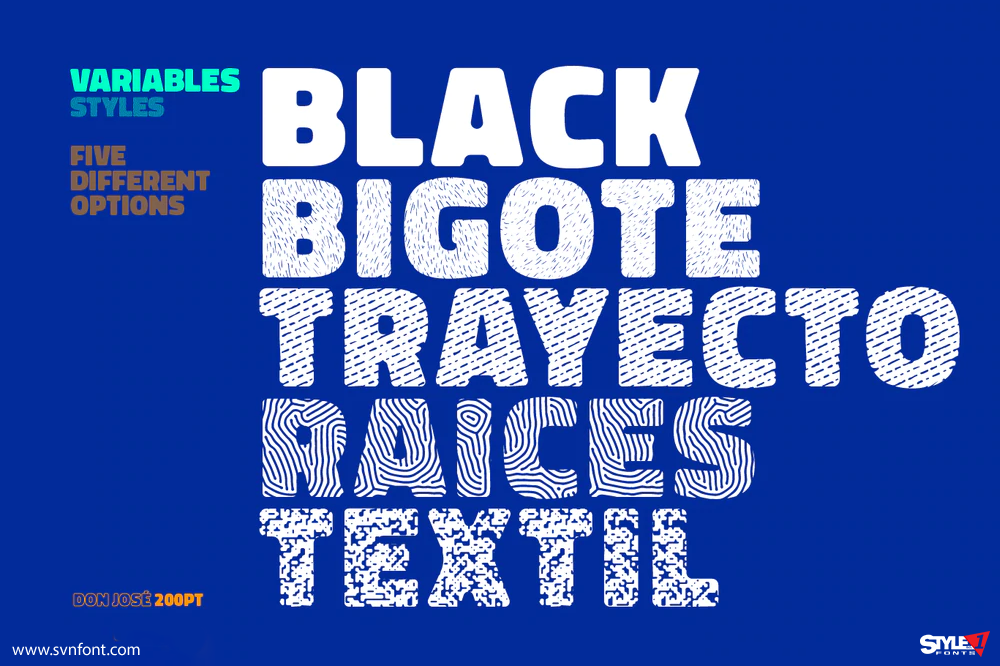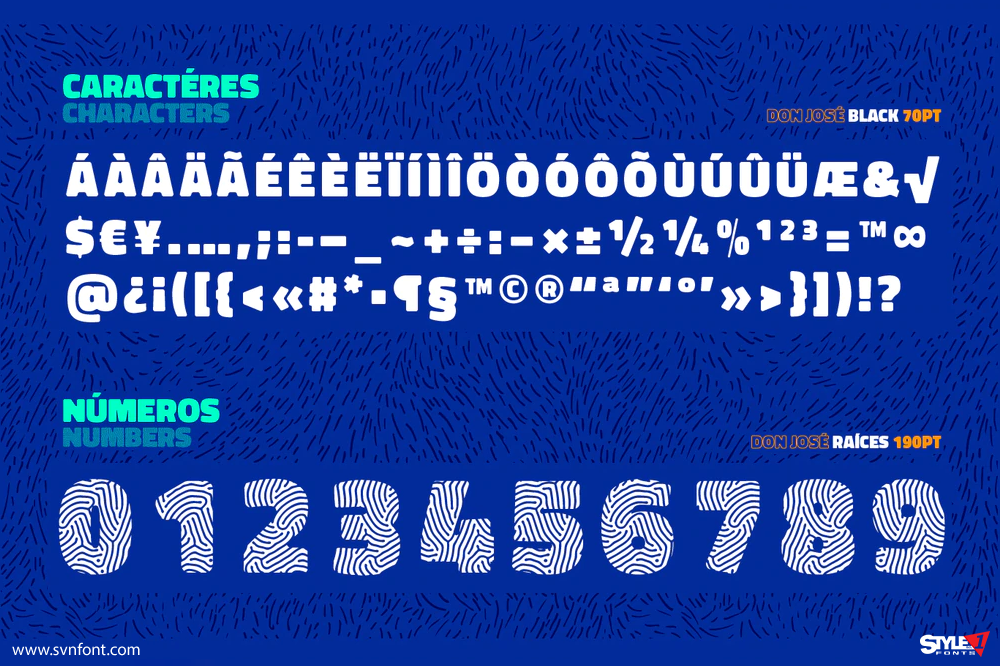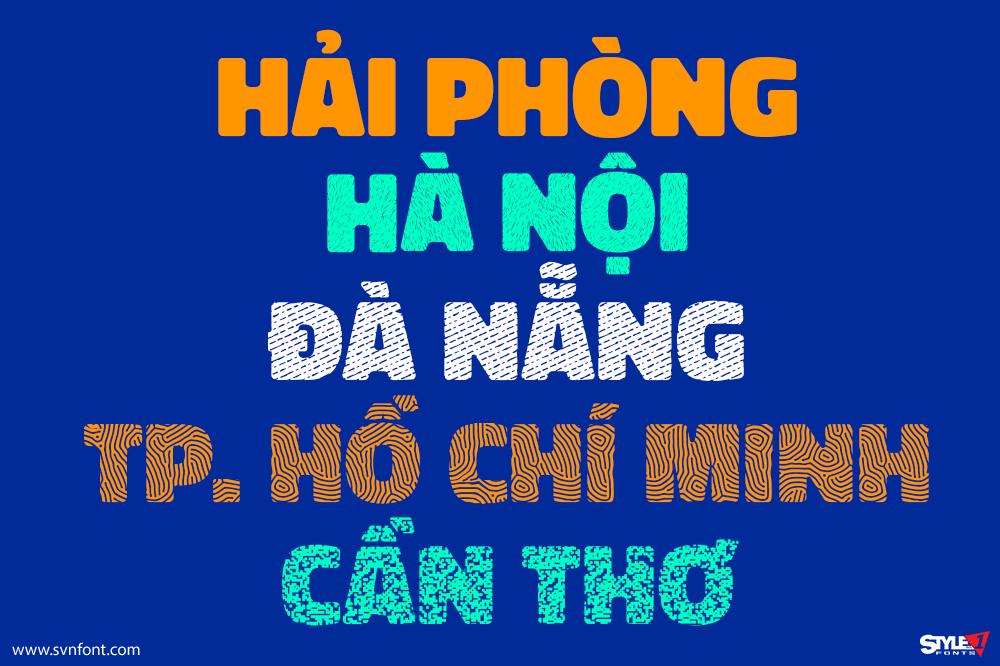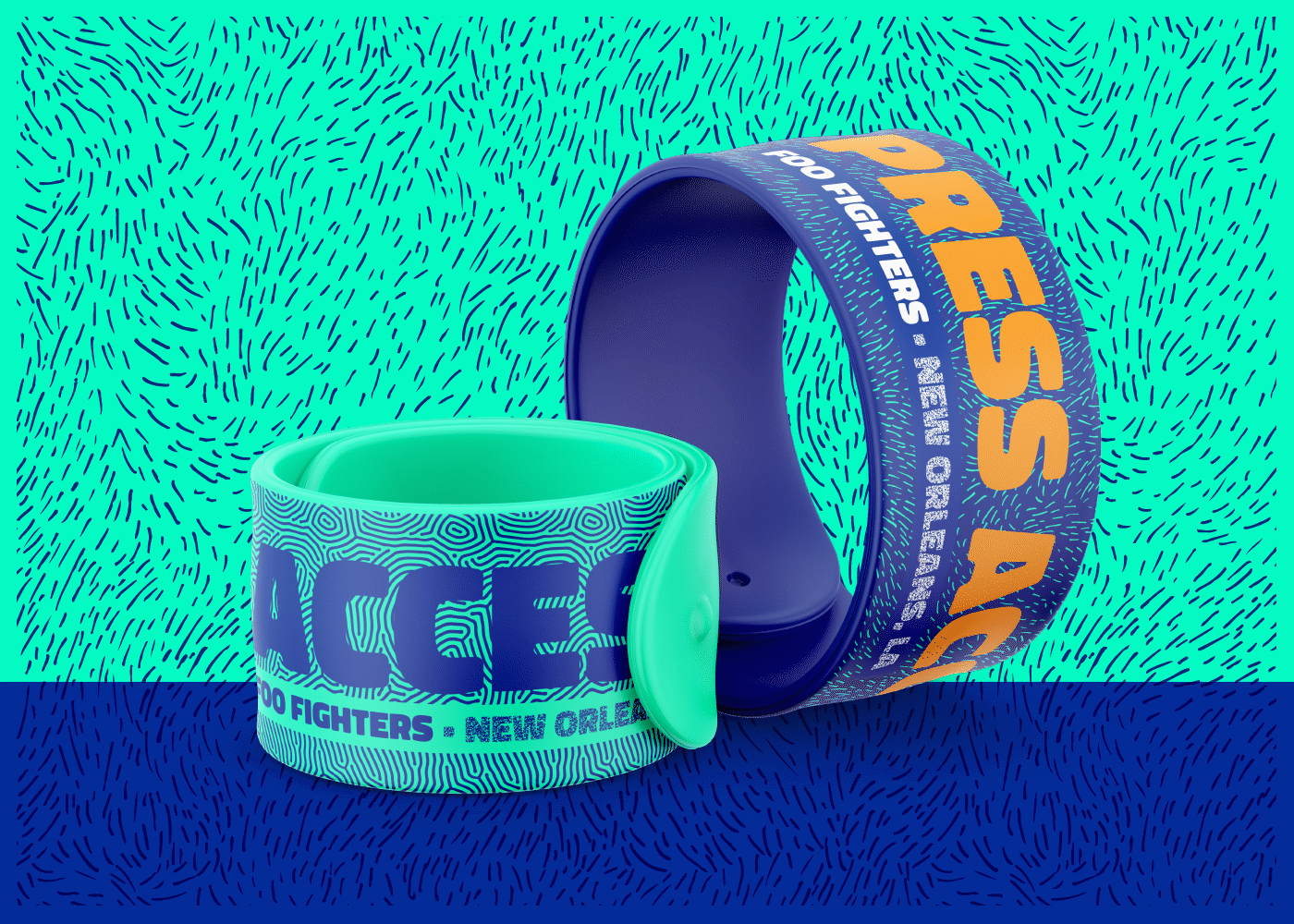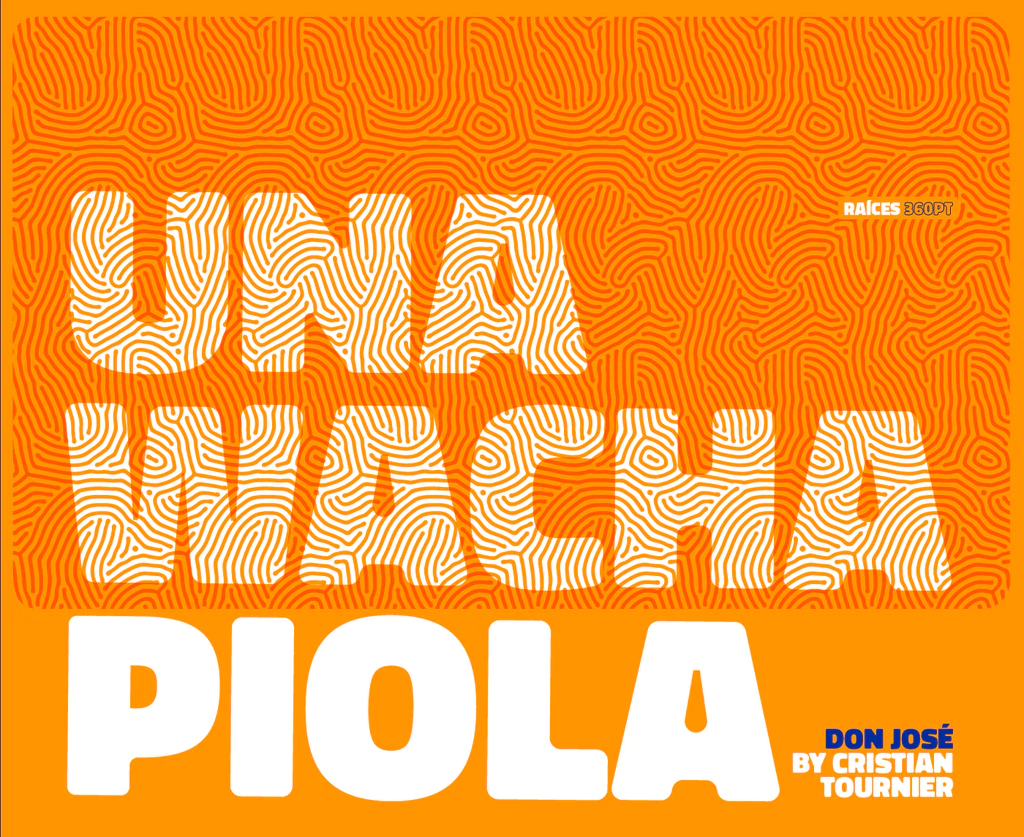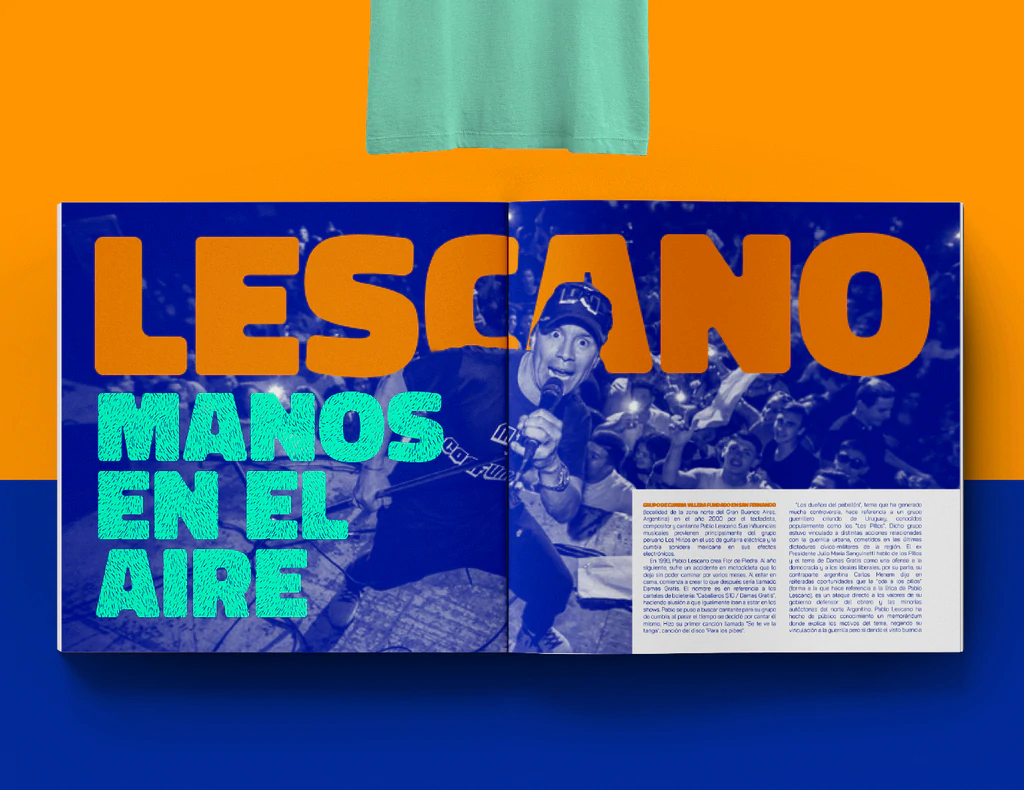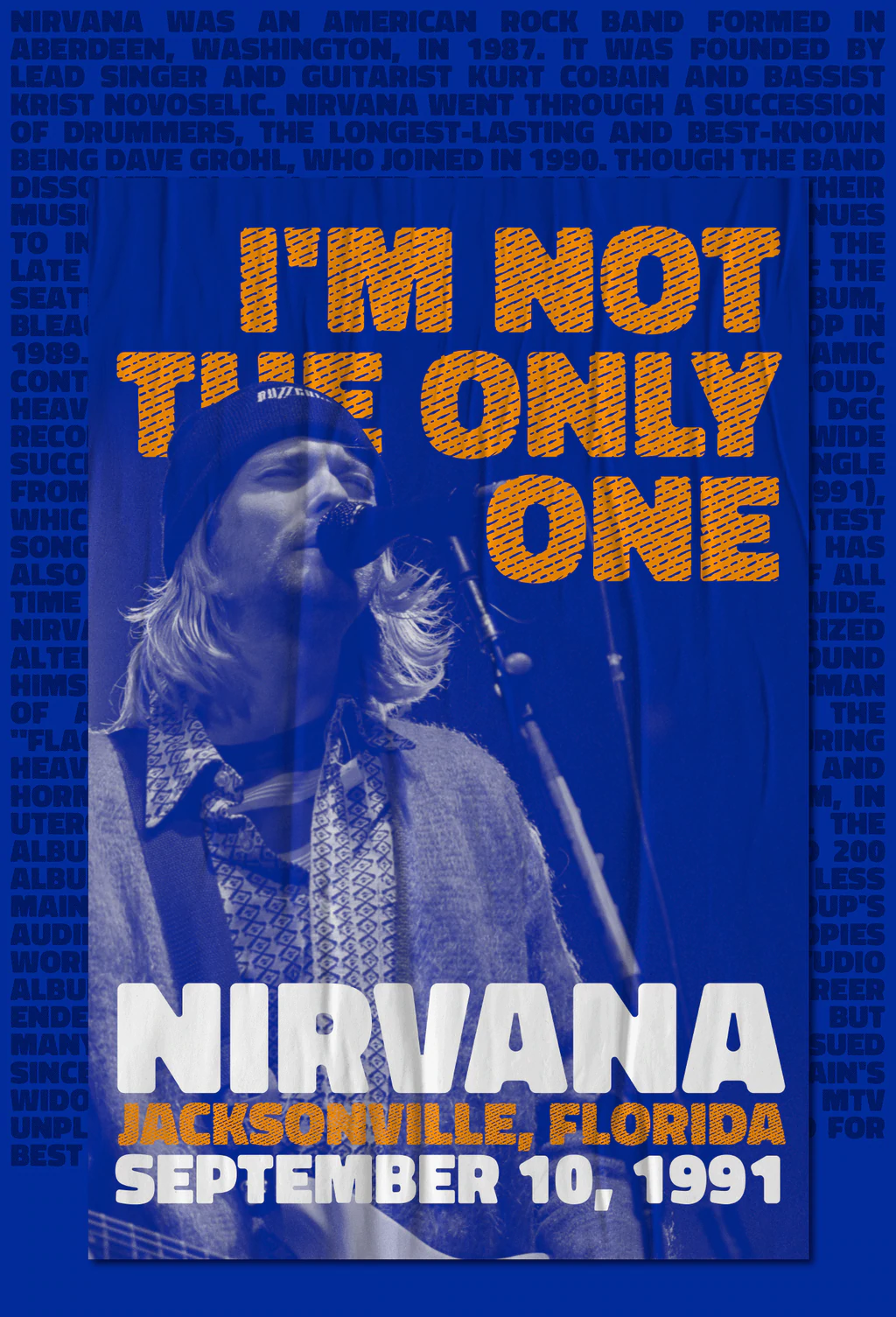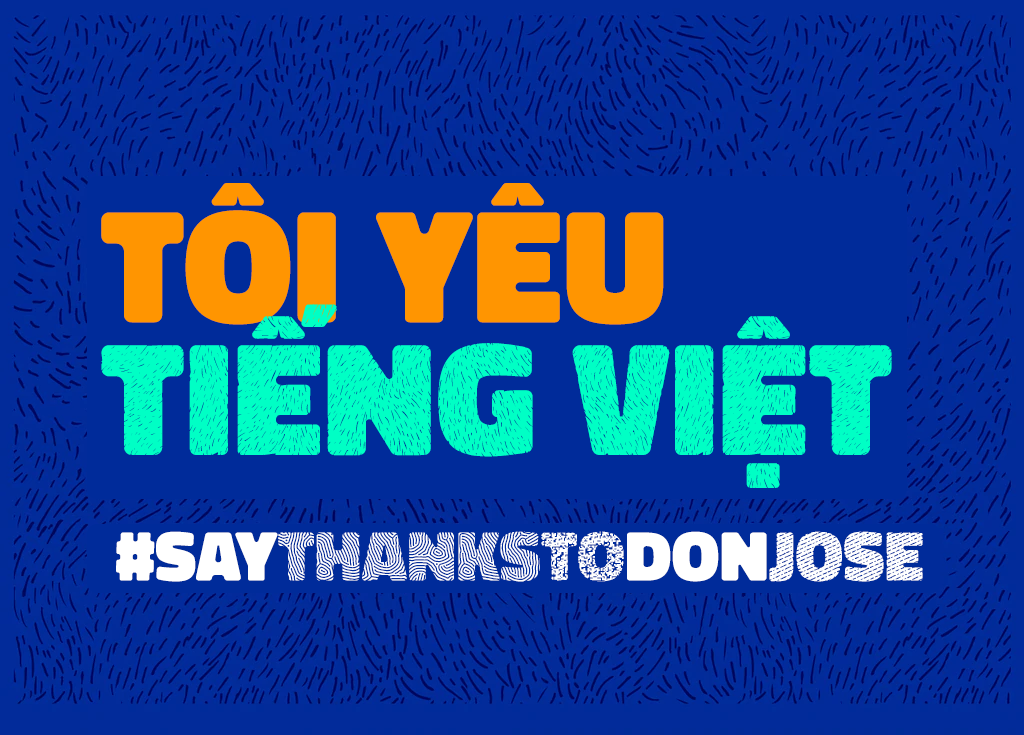
Don José, từ Cristian Tournier, là một họ phông chữ sans-serif có chiều cao x lớn, được thiết kế cho các tiêu đề. Họ phông chữ này bao gồm 5 kiểu: Black, Roots, Mustache, Journey và Textile. Don José rất phù hợp cho nhiều mục đích sử dụng bao gồm nhưng không giới hạn ở: tiêu đề bắt mắt, áp phích, quần áo, trích dẫn và tựa đề.
Nhà thiết kế: Cristian Tournier
Nhà phát hành: Cristian Tournier